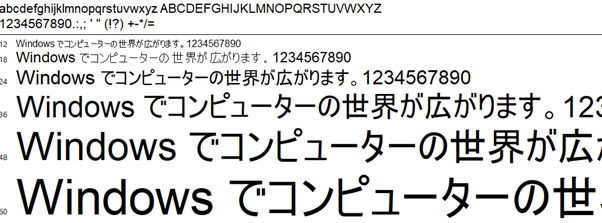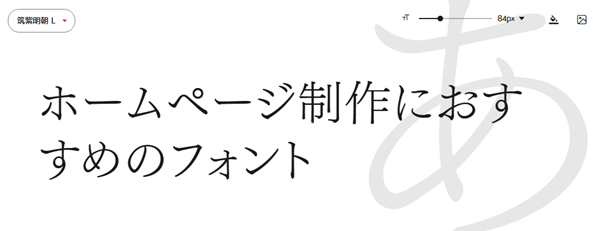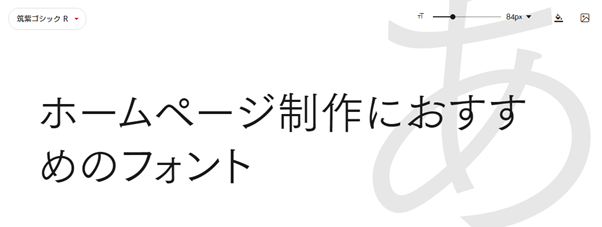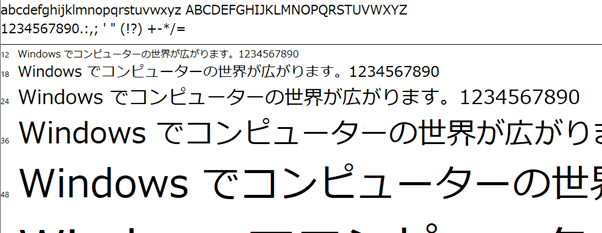
ホームページの印象を決めるフォント!おすすめフォントと選び方のポイント
ホームページを制作する際、どのようにフォントを選んでいますか?
フォント選びは、ホームページの印象を決定づけ、テキストの読みやすさや見やすさを左右する重要な要素です。一言でフォントと言ってもさまざまな種類があり、フォントを変更するだけでホームページの印象はガラッと変わります。そのため、フォントを意識しないままホームページ制作を行ってしまうと、素人っぽさが払拭されず、野暮ったいイメージになってしまう恐れがあります。文字の力を最大限に活用するためにも、企業やブランドイメージ、コンセプトなどを意識して、フォントを選ぶようにしましょう。
今回は、フォントの種類やホームページ制作におすすめのフォントについて紹介します。ホームページ制作でうまくフォントを活用するために、まずはどんなフォントがあるのかを知っておきましょう。
ホームページ制作でよく使用されるフォントの種類
フォントとは、パソコンやタブレット、スマートフォンなどのデバイスで表示される「文字の書体データ」を指します。
ホームページ制作でよく使用されるフォントは、システムフォント・Webフォントの2種類です。それぞれにメリットやデメリットがあるため、特徴を理解してフォントを選ぶことが大切です。
システムフォント
システムフォントとは、パソコンやスマートフォンにもともと入っているテキストデータを表現できるフォントです。例えば、Windowsの和文フォントならメイリオや游ゴシック、macではOsakaやヒラキノ角ゴなどが有名です。
デバイスにもともと内蔵されているフォントを使用するため、ライセンスを気にする必要がなく、データを個別にアップロードする手間がかかりません。また、Webフォントと比較し、サーバーにあるフォントデータを読み込まずに文字を表示できるため、表示速度が速くなります。
メリットの多いシステムフォントですが、フォントの選択肢が少なく、ユーザーの閲覧環境によっては表示されるフォントを統一させることができないため、デバイス間の印象がばらばらになってしまう恐れがあります。
Webフォント
Webフォントとは、Webサーバーから取得したフォントデータを、Webブラウザー上でテキストデータとして表示できるフォントを指します。Google FontsやFONTPLUSなどのWebサービスを使用して表示させる方法と、自作フォントをサーバーにアップデートして表示させる方法があります。
Webフォントは、有償でフォントを購入したり、インストールすることで利用できます。提供されるフォントは何でも使用していいというわけではなく、ビジネスとして利用する場合には商標利用可能なものを選択する必要があります。現在は、さまざまなWebフォントのサービスがあり、なかでも英語のフォントは無数に種類があります。
Webフォントを提供しているサービスは、下記が有名です。
• Adobe Fonts(アドビフォント)
• Google Fonts(グーグルフォント)
• Fontworks(フォントワークス)
• FONTPLUS(フォントプラス)
• 字游工房(じゆうこうぼう)
• モリサワ
ユーザーの閲覧環境に左右されずに、統一されたフォントを表示させることができる反面、サーバーからフォントデータを読み込むため、表示速度が遅いといったデメリットが挙げられます。設定がシステムフォントに比べると複雑ですが「異なるデバイス間でも統一感のあるフォント」でホームページを表示できるため、デザインがブレずにアピールできます。
ホームページ制作でおすすめのフォント
ホームページ制作では、ユーザーがテキストを読み進めるにあたって、文字の可読性や視認性の高さを意識する必要があります。可読性や視認性が低いと、ユーザーは読みづらさを覚え、ページを離脱されてしまう恐れがあります。そのため、ホームページ制作では可読性や視認性の高さはもちろん、伝えたい内容や印象によってフォントを選んでいきましょう。
国内でよく使用されているフォントは、和文フォントと欧文フォントの2種類です。そのなかでも和文フォントでは、明朝体とゴシック体の2種類。欧文フォントでは、セリフ体とサンセリフ体、スクリプト体の3種類に分けられます。
ここでは、明朝体・ゴシック体・欧文フォントを中心に、ホームページ制作に適したフォントを紹介します。
明朝体
明朝体は飾り気があり、高級感・上品さ・誠実さなど大人っぽい印象を与えることができるフォントです。書道を連想させる、トメ・ハネ・ハライの飾りの部分が残されているため、可読性が高くなります。そのため、小説や説明文など長文を読ませる部分でよく使用されています。
• 人間の情緒が伝わりやすい
• 高級感・伝統感・上品な印象
• 文字の太さが不均等で視認性は低い
• 書道を連想させ、可読性が高い
ヒラギノ明朝
ヒラギノ明朝は、遠くからでも読みやすく、瞬間的に分かる視認性の高さが特徴です。どんな場面でも使用しやすく、シャープな印象を与えることができます。
ヒラギノ角ゴとの相性も良く、組み合わせて使用することができるため、汎用性が高いフォントと言えるでしょう。
また、Apple社のパソコンやスマートフォンのmacOSやiOSにも標準装備されており、Appleユーザーにはなじみの深いフォントです。しかし、WindowsOSにはインストールされていないため、使用するにはヒラギノ明朝を購入する必要があります。
游明朝
游明朝は、可読性が高くホームページ制作だけでなく、小説などでも使用されることの多い汎用性の高いフォントです。システムフォントとして指定しているサイトも多く、本文だけでなく見出しにも使用しやすくなっています。
シャープな印象で、現代的な印象と伝統的な印象を兼ね備えた明朝体です。
macOSとWindowsOSに標準装備されており、双方の環境で同じフォントの見せ方を実現できます。
リュウミン
リュウミンは、ウロコに柔らかさがあり、親しみやすく安定感のある印象を与えてくれます。macOSとWindowsOSに対応しており、双方の環境で同じフォントの見せ方を実現できます。
筑紫明朝
筑紫明朝は、Fontworksの書体デザイナーがデザインしたフォントです。一般的な明朝体と比較し、文字の中の空間が狭くなっており、品よくなめらかな印象を与えることができます。くせが少ないため、可読性が高くホームページ制作におすすめのフォントと言えるでしょう。
ゴシック体
ゴシック体は明朝体と比較し、均等な太さで安定感があり、親近感・カジュアル・安定感などシンプルで力強い印象を与えることができます。線の太さの強弱が小さく、くせが少ないため視認性が高くなります。小さい文字や本当に読んでほしいタイトルなどに使用するのに適しています。
• 文字の太さが均一で見やすい
• フォントが小さくても読みやすい
• 遠くから見ても分かりやすい
• 視認性が高い
メイリオ
メイリオは、日本語の「明瞭」に基づいており、視認性の高さが特徴です。太字にも対応しており、強調したい文字などに使用することで、フォントを変えずに自然に表現できます。WindowsOSに標準装備されており、幅広い世代で読みやすいオーソドックスなフォントと言えるでしょう。
游ゴシック
游ゴシックは、ビジネス用途に適しており、硬い雰囲気を演出できるフォントです。
macOSとWindowsOSに標準装備されており、双方の環境で同じフォントの見せ方を実現できます。しかし、スマートフォンのAndroidOSやiOSには標準装備されていないため、スマートフォン対応のホームページを制作する際は注意しましょう。
ヒラギノ角ゴ
ヒラギノ角ゴは、ヒラギノ明朝との組み合わせを意識してデザインされたフォントです。Apple社のパソコンやスマートフォンのmacOSやiOSにも標準装備されており、Appleユーザーにはなじみの深いフォントです。しかし、WindowsOSにはインストールされていないため、使用するにはヒラギノ明朝を購入する必要があります。
視認性と存在感を両立でき、ホームページ制作だけでなく、書籍やテレビCMなどでも幅広く使用されているフォントです。汎用性が高く、見出しや本文など多用途で活用できます。
筑紫ゴシック
筑紫ゴシックは、一般的なゴシック体よりも柔らかな印象になり、温かみを感じられる上品なフォントです。
筑紫ゴシックは有料フォントとなるため、使用するには購入か定額サービスの導入が必要です。
コーポレートロゴ
コーポレートロゴはフリーフォントとなっており、macOSとWindowsOSの主なバージョンに対応しています。コーポレートサイトやホームページのロゴ制作などに向いており、視認性が高く、シンプルで安定感のある印象を与えてくれます。
欧文フォント
欧文フォントは、大きく分けて3種類あります。
種 類 説 明
セリフ体 ・文字の線端に、ウロコのような飾りがついている
・可読性が高い
・和文書体でいうところの明朝体サンセリフ体
サンセリフ体 ・飾りがついていない
・カチッとした印象
・直線・曲線が美しい
・和文書体でいうところのゴシック体
スクリプト体 ・筆記体のようなフォント
・デザイン性が高い
・可読性は低い
そのなかでも、有名なHeleveticaとArialを紹介します。
Helevetica(ヘルベチカ)
CHANELのロゴや、世界中の空港や駅などの公共施設などのパブリックデザインが必要な場面でよく使用されているHelevetica。世界で最も広く使用されている人気の定番フォントです。
Heleveticaは特徴的な形やラインがなく、くせがないため非常に読みやすく、どんなホームページにも合わせやすい非常に汎用性の高いフォントです。欧文フォント選びに悩んだら、まずはHeleveticaを抑えておくようにしましょう。
また、HeleveticaはApple社のパソコンやスマートフォンのmacOSやiOSにも標準装備されています。WindowsOSの場合は、別途インストールが必要になります。
Arial
macOSとWindowsOSに標準装備されており、双方の環境で同じフォントの見せ方を実現できます。Windowsでは標準装備されていない上述のHeleveticaの代替えとして、類似性の高いArialを利用してもいいかもしれません。Arial自体もデザインにくせが少なく、汎用性が高いフォントと言えるでしょう。